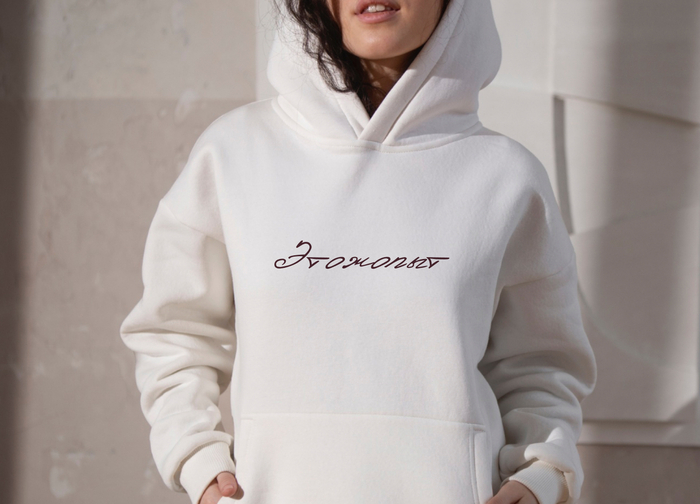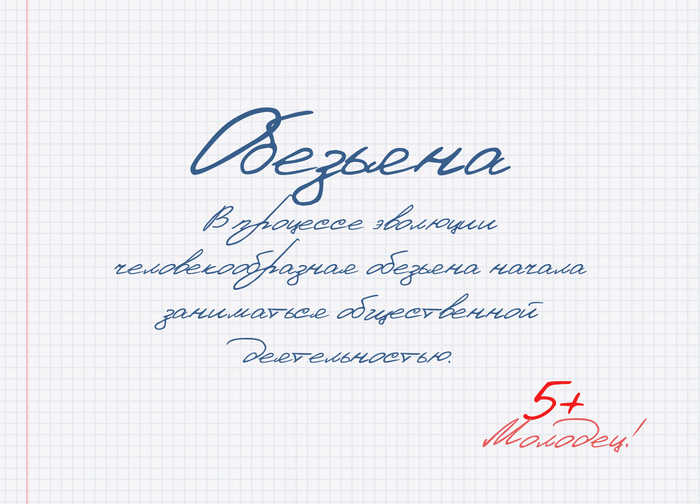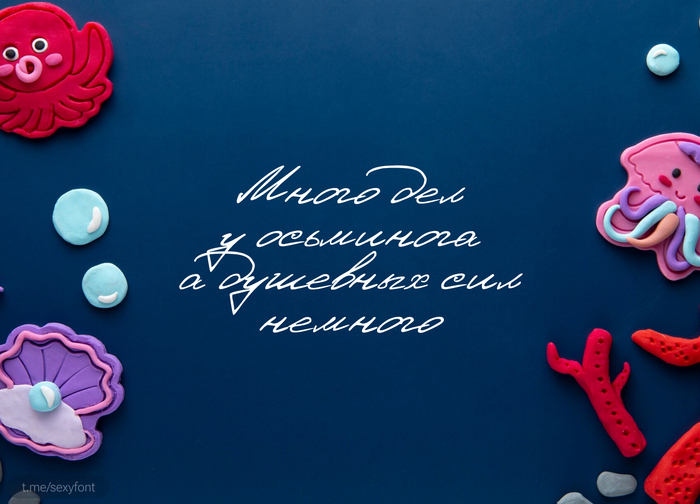
Шрифт Denistina
Рукописный шрифт как со школьной тетради) В меру аккуратный. Использовать только в коротких фразах. Как и большинство подобных шрифтов читаемостью не блещет.